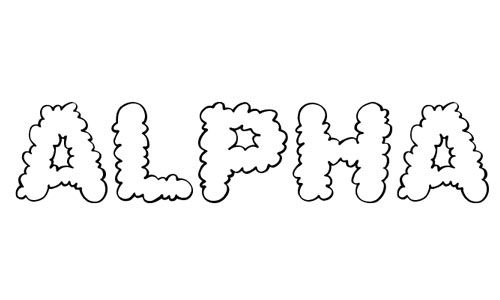
BOMB
BOMB — это декоративный шрифт, разработанный Билли Аргелом. Этот классный шрифт бесплатен только для личного использования, он отвечает многим требованиям дизайна и хорошо смотрится на ваших работах.
Turds
шрифт turds от Xerographer Fonts поставляется с двумя разными стилями и называется детским шрифтом. если вы хотите использовать этот шрифт в коммерческих целях, вам необходимо получить лицензию.
PooCorny
PooCorny — контурный шрифт с двумя разными стилями, созданный Gaut Fonts.![]()